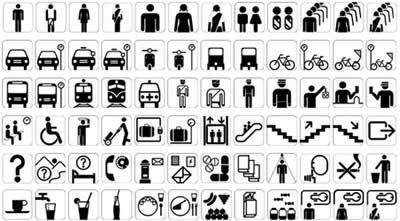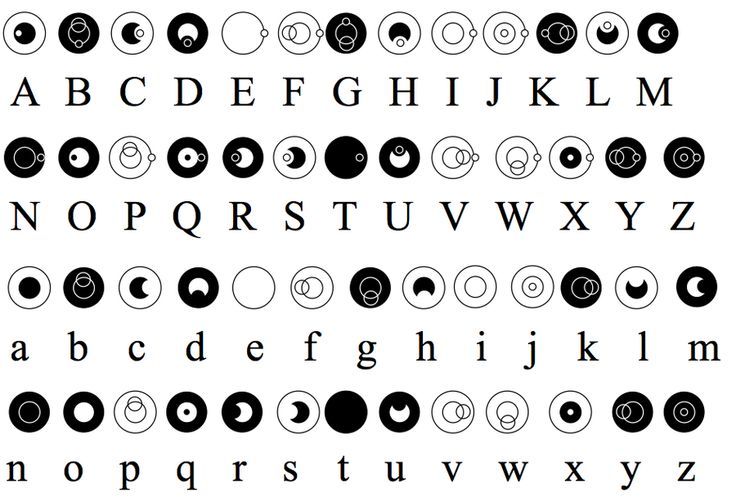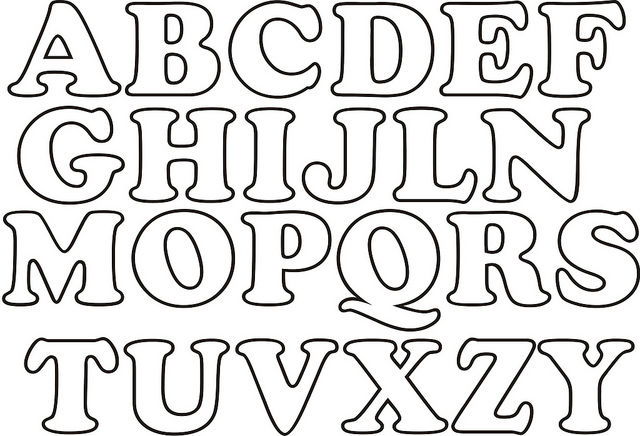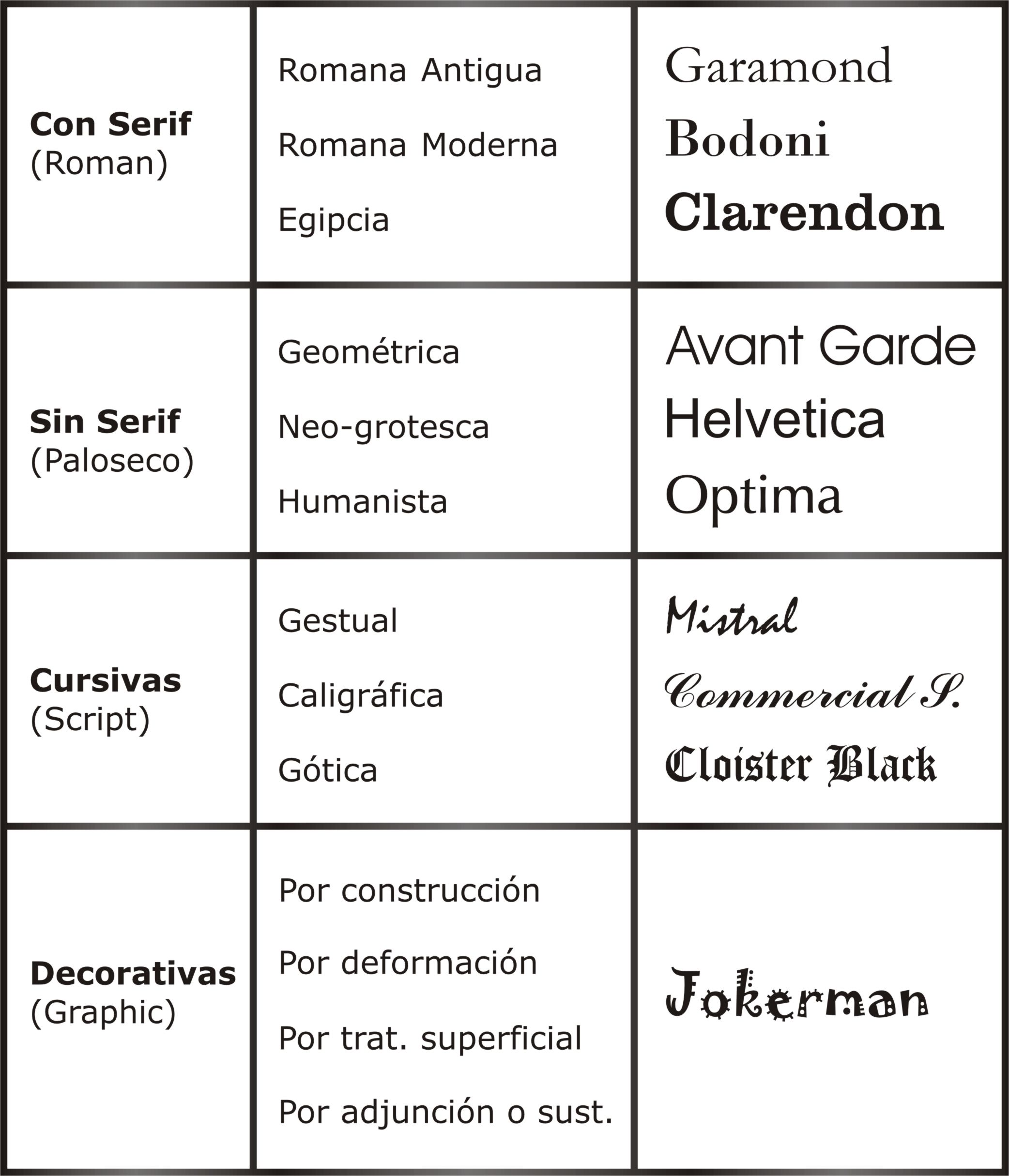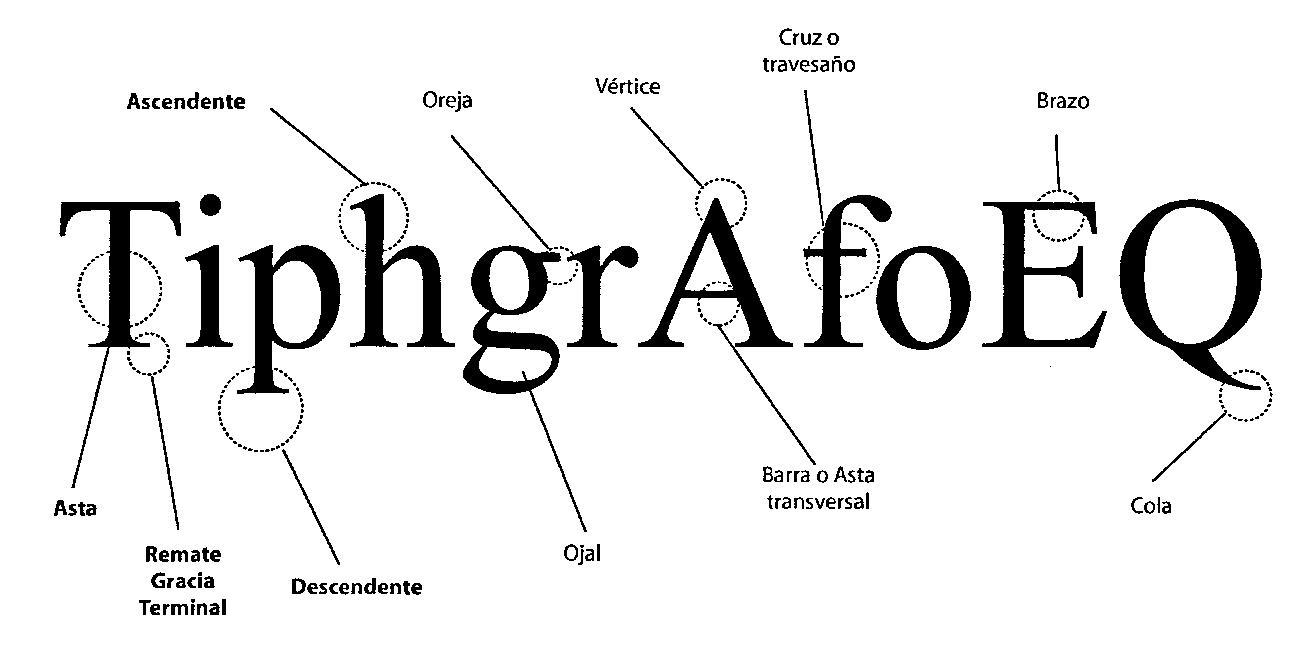
La Tipografia
Es el fiel reflejo de una epoca , por ello la evolucion del diseño de las mismas responde a proyecciones tecnologicas y artisticas
Conceptos
Letra
signo , representacion grafica del lenguaje hablado
tipografia
es el arte de diseñar letras y compiner texto de tal modo que puedan leerse de un modo facil , eficaz y agradable
Desarrollo historico de la escritura
Desarrollo de la escritura
Pictogramas
Mutacion a una forma alfabetica
variaciones del alfabeto
Estructura de la letra
Los caracteres pueden presentarse en :
capitales
minusculas
numeros
versalitas
Partes de una letra
asta
parte principal de una letra que la define como su forma
astas montantes
astas principales u oblicuas de una letra
anillo
asta de curva cerrada
Brazo
parte terminal que se proyecta horizontalmente
cola
parte oblicua colgante en direccion ascendente
ojo
espacio en blanco que queda en el interior de las letras
clasificacion Tipografica
La presencia o ausencia del serif o remate
se forma el serif
la relacion curva o recta entre bastones y serifs del grosor del trazo
la uniformidad o variabilidad
la direccion del eje de engrosamiento
variables visuales
amplitud
extension de la letra
forma
relativo a la estructura
tamaño
definido como altura/cuerpo
tono
modifica el grosor de la letra
inclinacion
inclinacion de los ejes de la letra
Fuentes y Familias Tipograficas
fuente tipografica
estilo , apariencia de un grupo de caracteres
Familia Tipografica
tipos basados en el mismo tipo
medidas tipograficas
letra
signo
tamaño de la letra
cuerpo, se mide en puntos
linea
conjunto de letras acomodadas
interlinea
espacio entre una linea y otra
profundida
longitud de la linea
justificacion
ancho de una columna